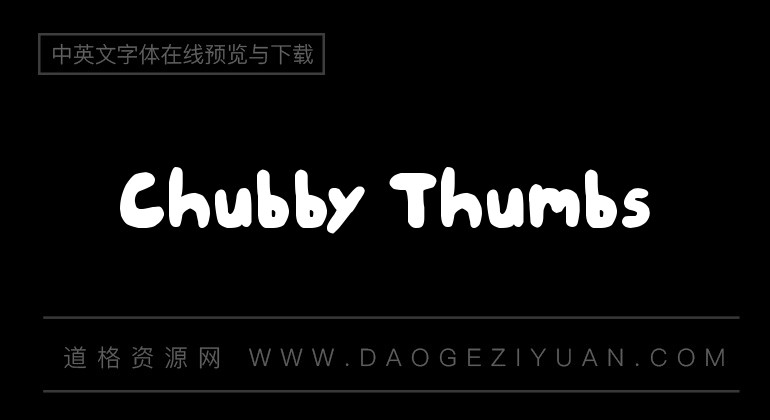
Chubby Thumbs
Chubby Thumbs 是一款粗体手写字体,它具有粗犷的外观和活泼的风格,适合用于各种卡片、海报、标识、商标等设计中。该字体采用自然的笔触,具有温暖的质感,能够传达出温情、友善、活泼的气氛。Chubby Thumbs 字体具有许多不同的字形,能够满足不同的设计需求,其中包括大写字母、小写字母、数字和标点符号。
Chubby Thumbs是一款非常不错的手写艺术字体,具有很好的视觉感,适合于文化类的宣传设计、商业类品牌的广告和产品包装设计以及个性化文字排版等较多场景。